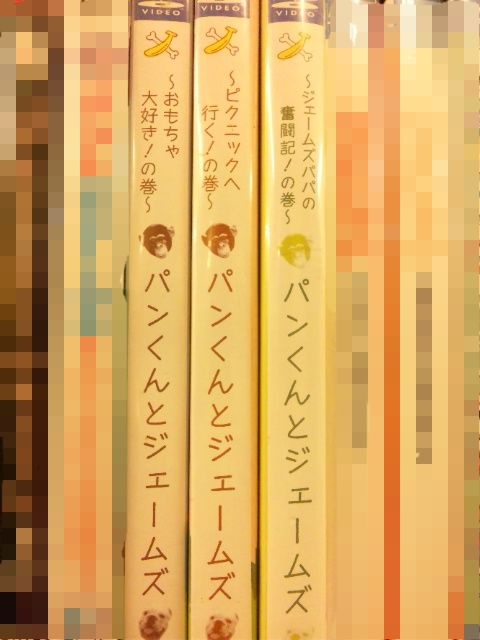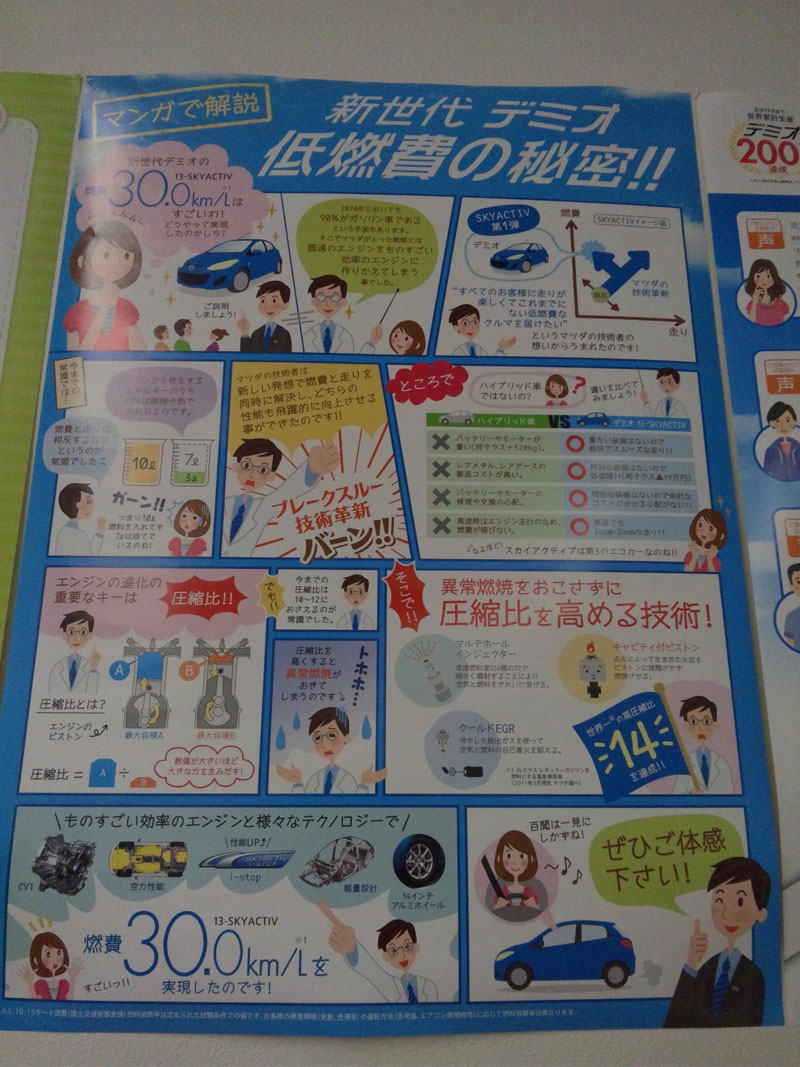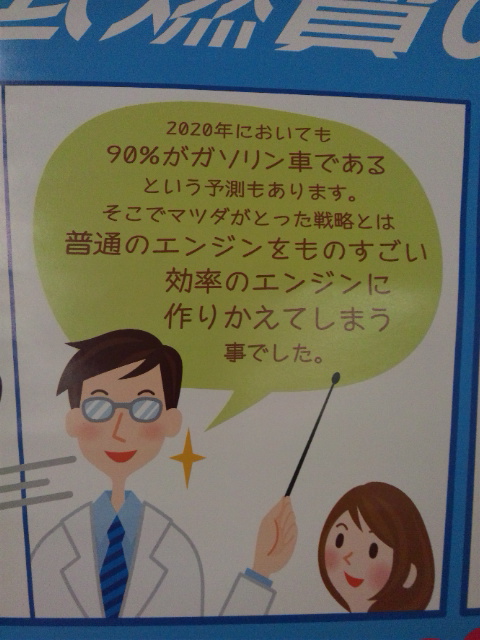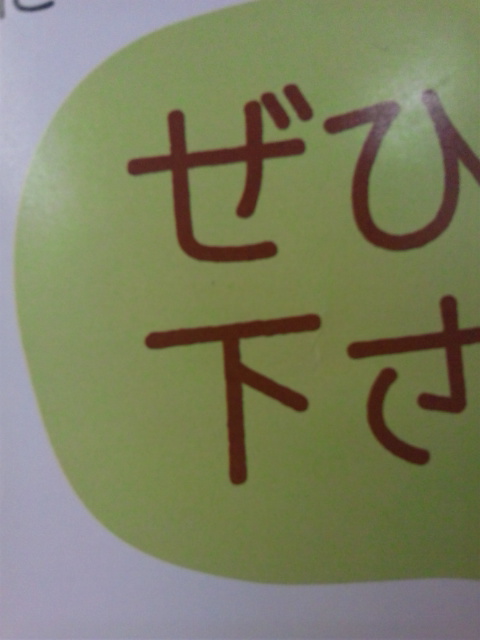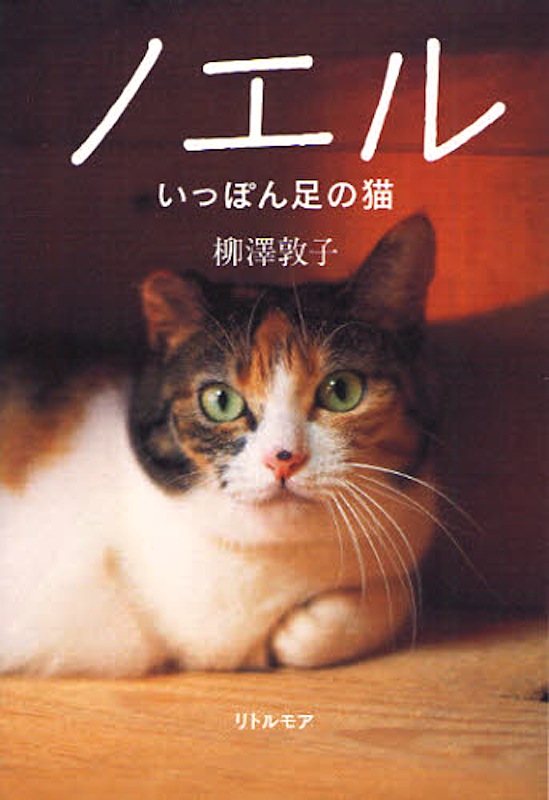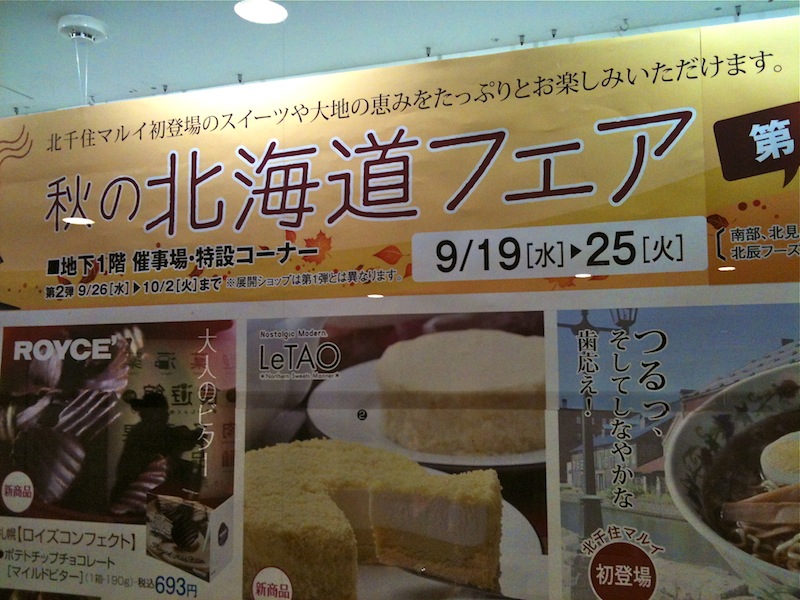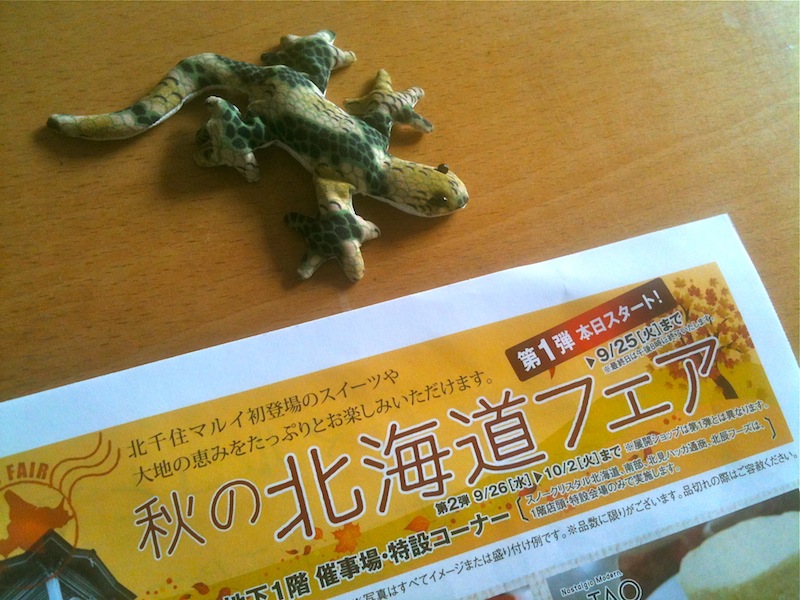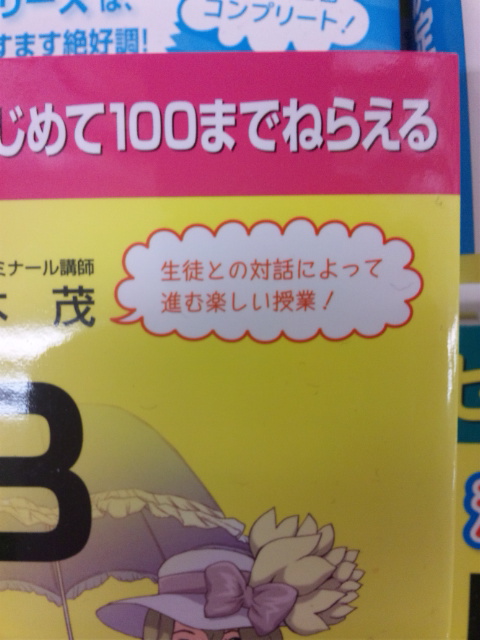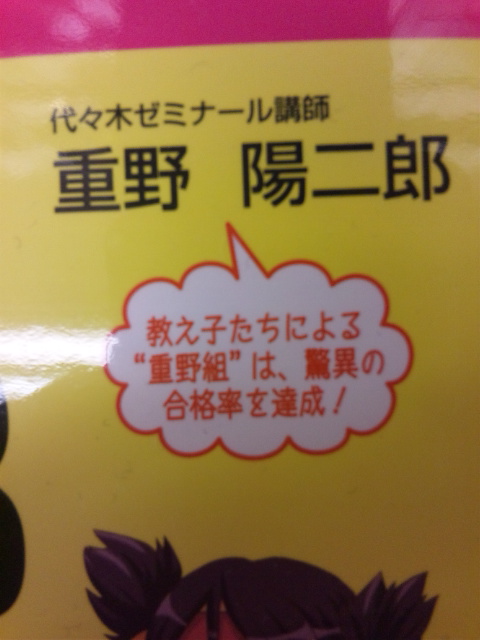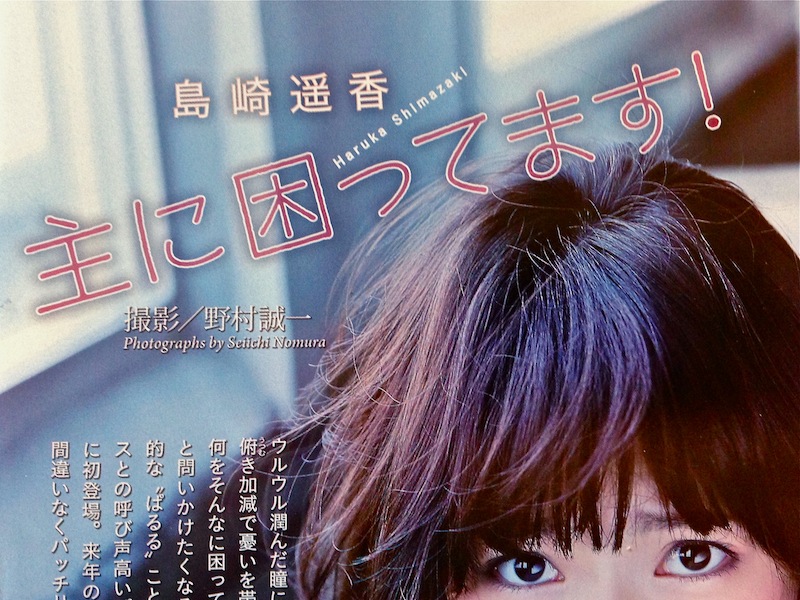
クノールクラブ「スープの秘密」  takumi  2014年6月9日(月) 17:20
クノールクラブ(http://knorr-club.jp/)のページに貼られていたバナーでセプテンバーが使われていました。
バナーのリンク先(http://knorr-club.jp/brand/secret)でも、ちょこちょこセプテンバーが使われているようです。
takumi  2014年6月9日(月) 17:21 [修正]
もうひとつ。
さとうゆたか  2014年6月9日(月) 21:12 [修正]
いま制作中の2ウェイトが完成して4ウェイトになれば、使われる場がもう少し増えるかもしれませんね…。
エステティックサロンのCM  さとうゆたか  2014年4月21日(月) 9:34
ミランダ・カーが出演している、たかの友梨ビューティクリニックのテレビCM。
さとうゆたか  2014年4月21日(月) 9:36 [修正]
この書体をテレビで見るのは久しぶり…。
絵本の表紙  さとうゆたか  2014年3月3日(月) 16:14
書名:ぼくは ここにいる
著者:ピーター・レイノルズ
翻訳:さかき たもつ
発行:小峰書店
フランス語参考書にセプテンバー  てなしも  2014年1月13日(月) 0:45  HP
表面が滑らかにアウトライン化されていたため印象が変わり投稿していいものかしばらく迷いました。
三修社「CD2枚付 ちょこっとわがままフランス語」タイトルにセプテンバーが使われています。
さとうゆたか  2014年1月13日(月) 8:29 [修正]
セプテンバーの使用例は少ないので、助かります。
2文字並んだ「まま」、なぜか左の字の最終画が短くなってます…ね。アウトライン化した後で太くされているので、その時の作業で意図的にやったものかどうかは判りませんが…。
takumi  2013年11月4日(月) 18:56  HP
ブログのタイトル画像に使用しました。
セプテンバーは2年ちょっと前に『フォントパック2008』で購入したのですが、あまり使う機会がありませんでした…。
今あるL・Mウェイトの2つだと、印刷ではよいのですが、ディスプレイでの表示となるとちょっと細くて物足りないかな、という感じです。
より太いウェイトのセプテンバーの完成を楽しみにしております(笑)。
さとうゆたか  2013年11月4日(月) 21:20 [修正]
私も同じように「ちょっと細くて物足りない」と感じており、もう少し太いウエイトの制作に2010年から取り組んでいます。
漫画単行本の広告  さとうゆたか  2013年10月6日(日) 16:24
村上もとかがビッグコミックオリジナルに連載中の「フイチン再見!」。
単行本第1集の広告の一部。
てなしも  2013年6月30日(日) 20:29  HP
浅草ツバメノートさんがリュウド株式会社とコラボした大学ノートシリーズ「Thinking Power Notebook」新製品バナーに「セプテンバー」が使われていました(URLはHP欄)。
さとうゆたか  2013年6月30日(日) 22:13 [修正]
←この画像ですね。
小説の題名  さとうゆたか  2013年6月29日(土) 16:37
掲載誌:本の旅人
題名:最近、空を見上げていない
著者:はらだみずき
発行:角川書店
巻頭グラビアタイトル  さとうゆたか  2012年12月11日(火) 15:32
ビッグコミックスピリッツという週刊雑誌の最新号。